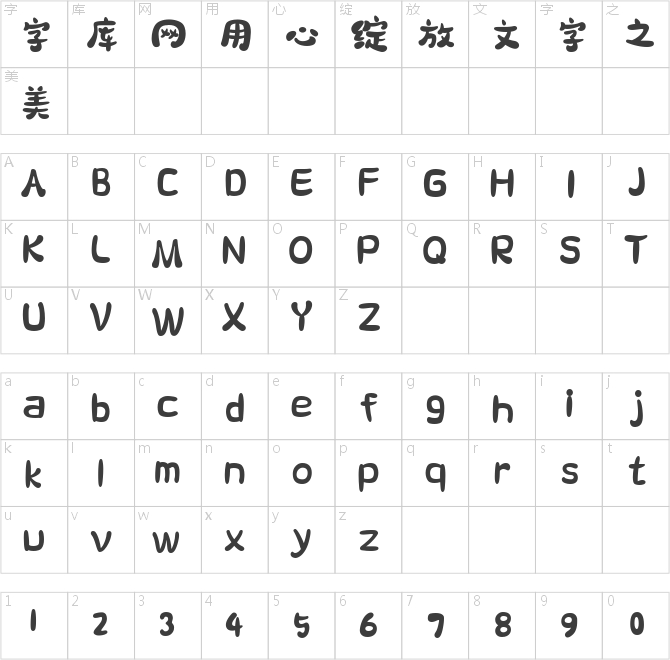
隨著造字計(jì)劃的進(jìn)行,酷貝街打造的“一品字庫”也隨之上線多款字體供廣大網(wǎng)友使用。而為了照顧到廣大網(wǎng)友,一品字庫于8月27日正式上線“一品包裝體”供所有人免費(fèi)學(xué)習(xí)使用!注意:商業(yè)用途請購買商用授權(quán)!
一品包裝體字體字庫是一款讓人賞心悅目、百看不厭的中文字體,適合各類廣告和產(chǎn)品包裝設(shè)計(jì)應(yīng)用,字體大小6.92MB,格式為ttf字體,上傳用戶是FaYu,作者/版權(quán)方為一品字庫